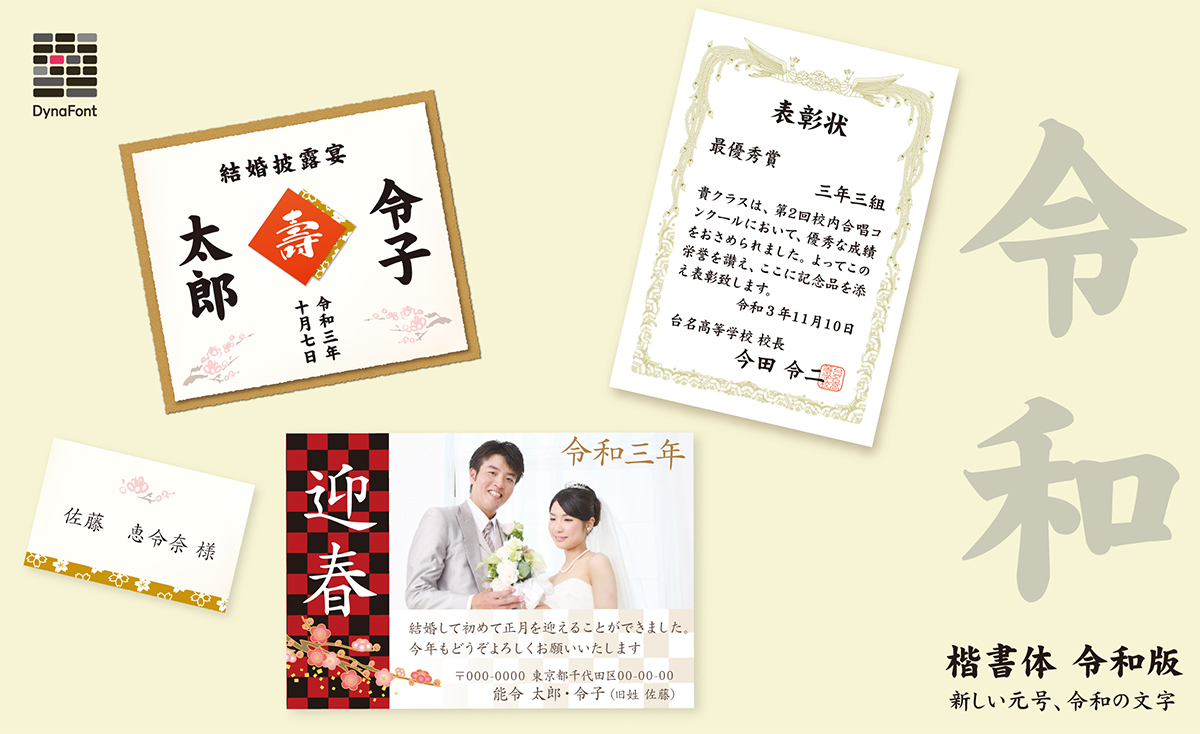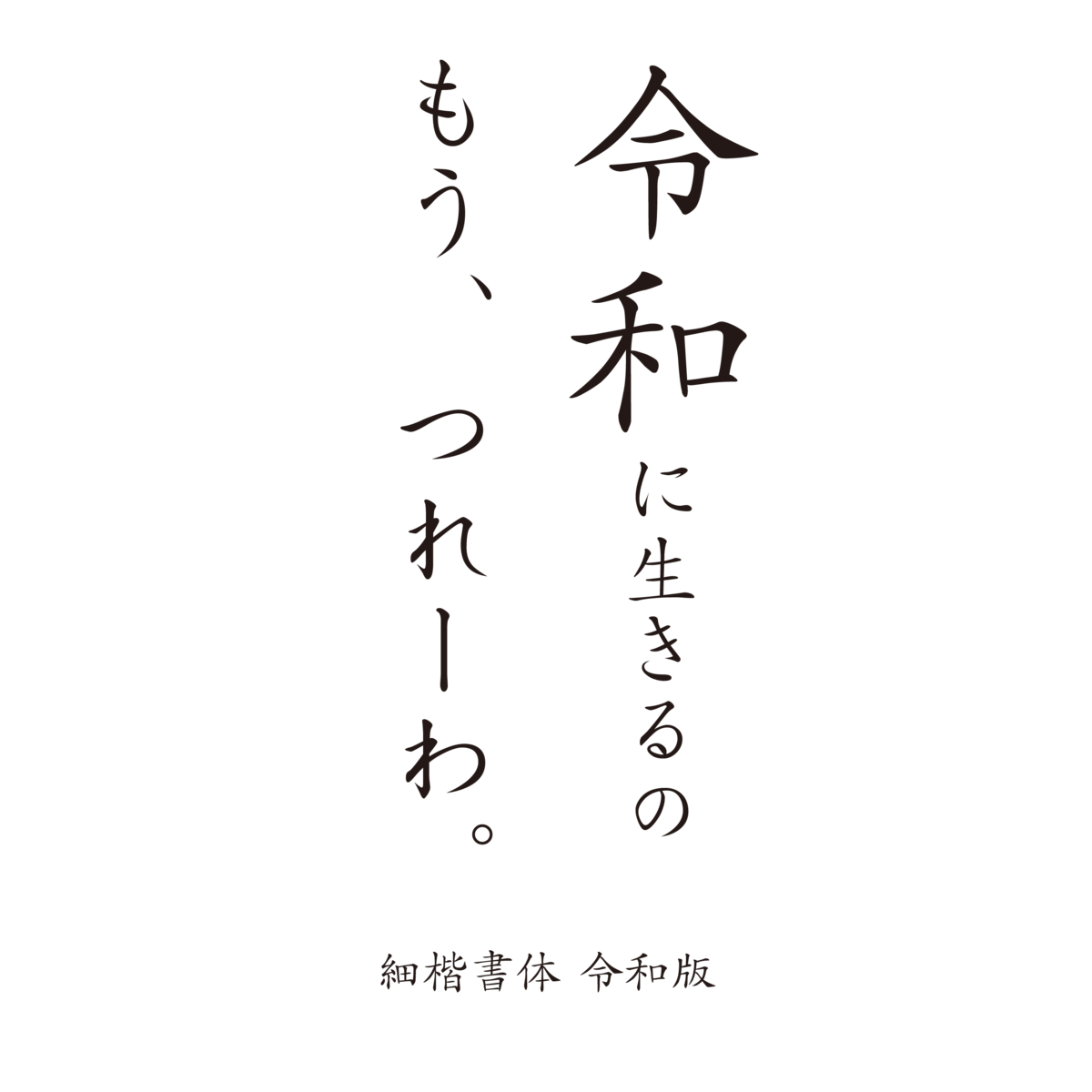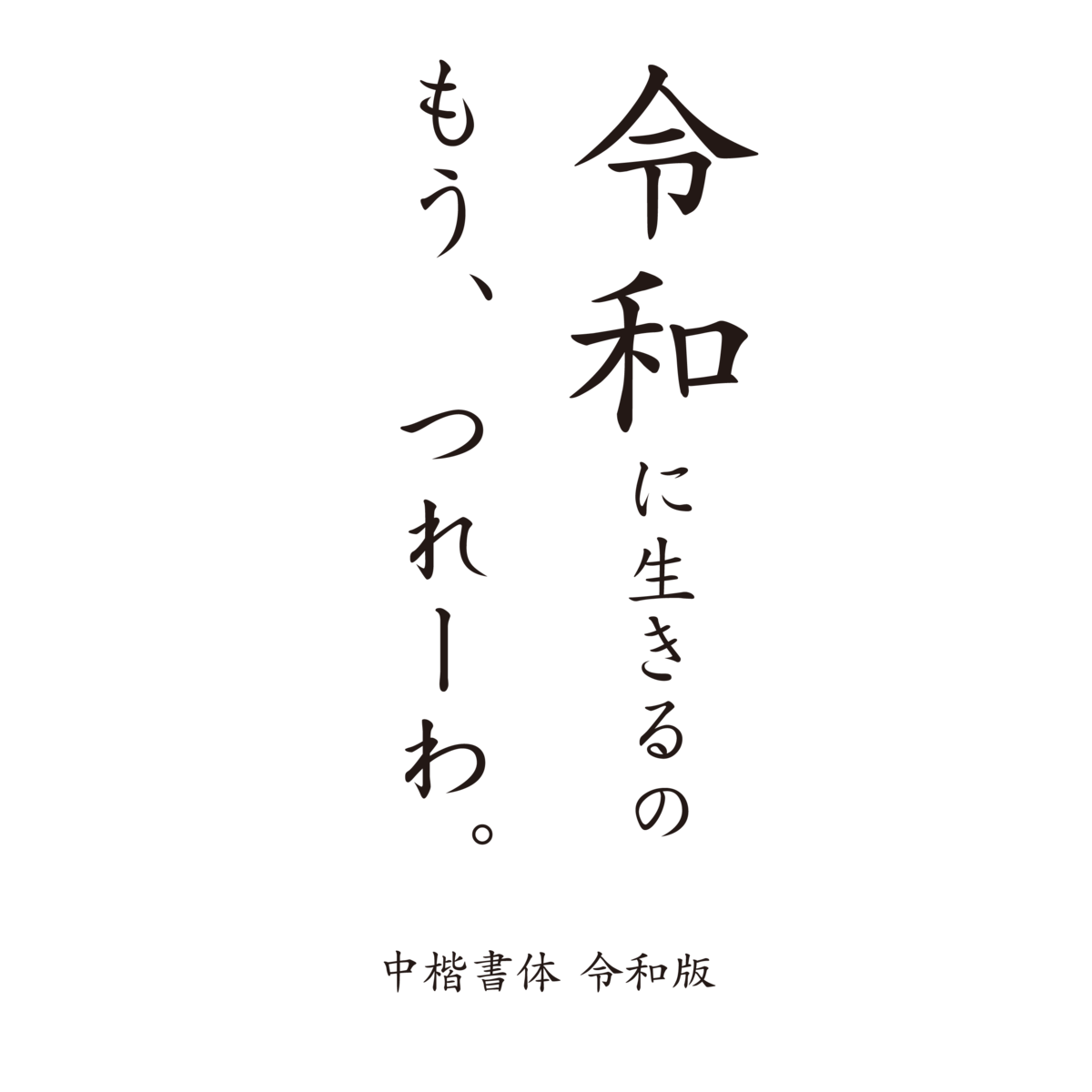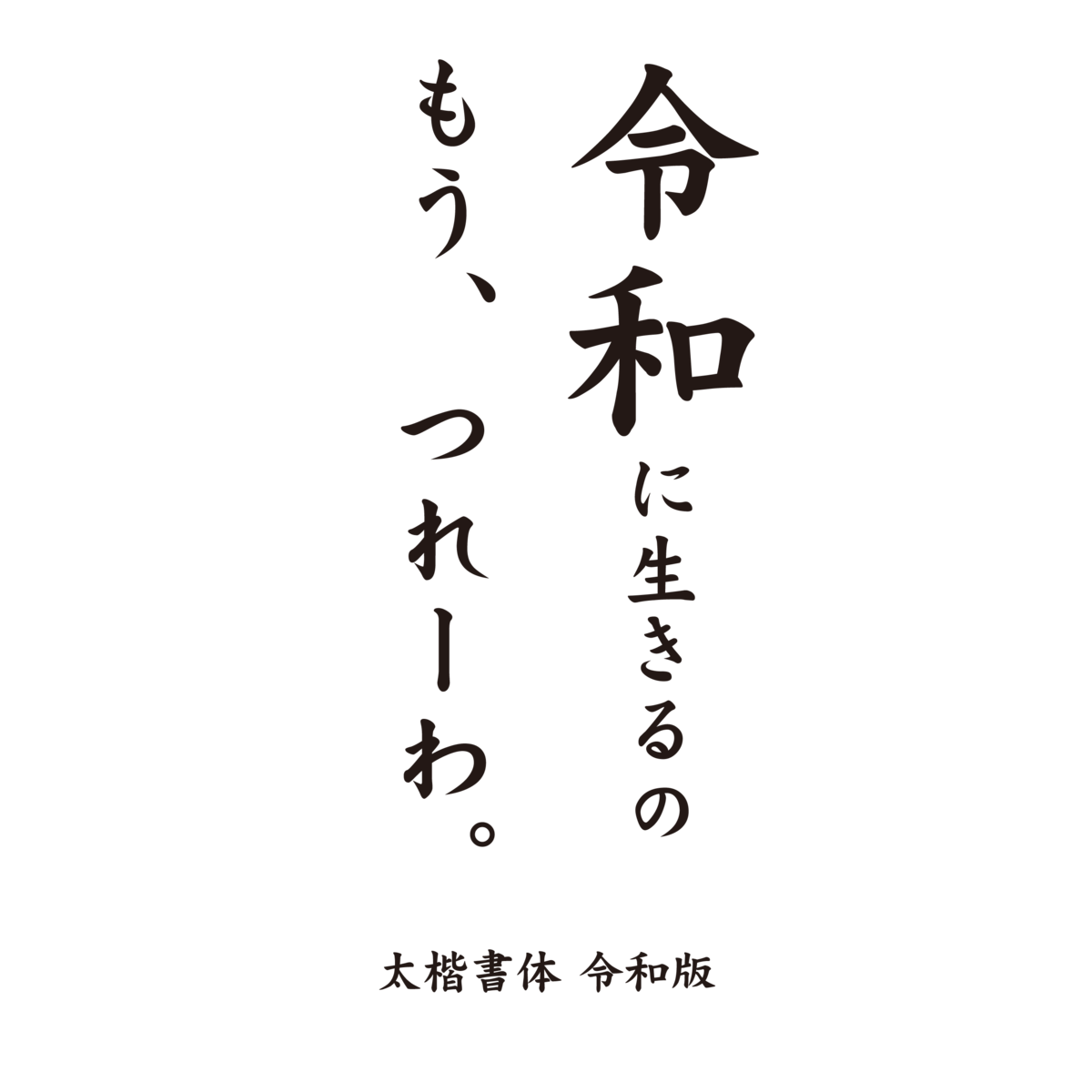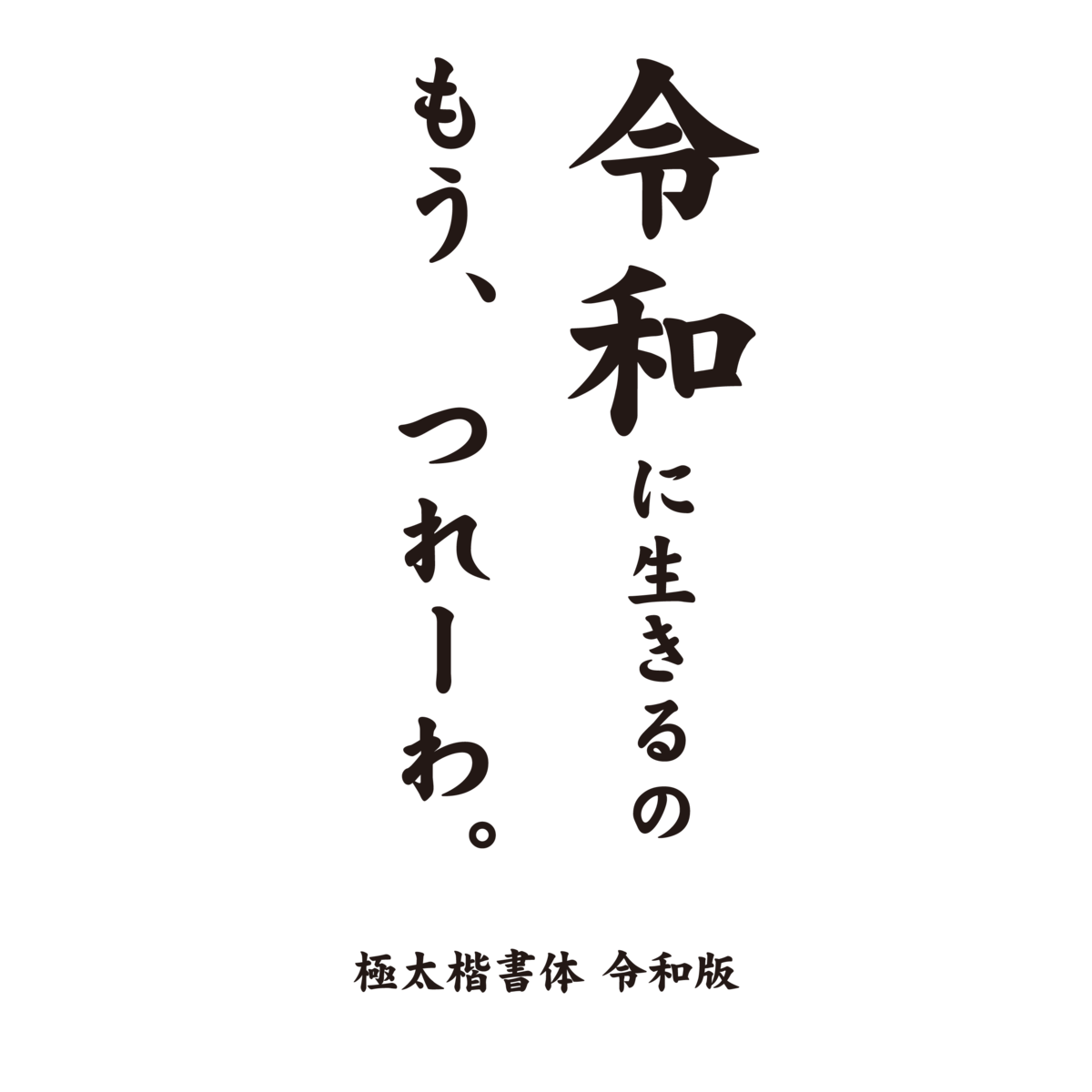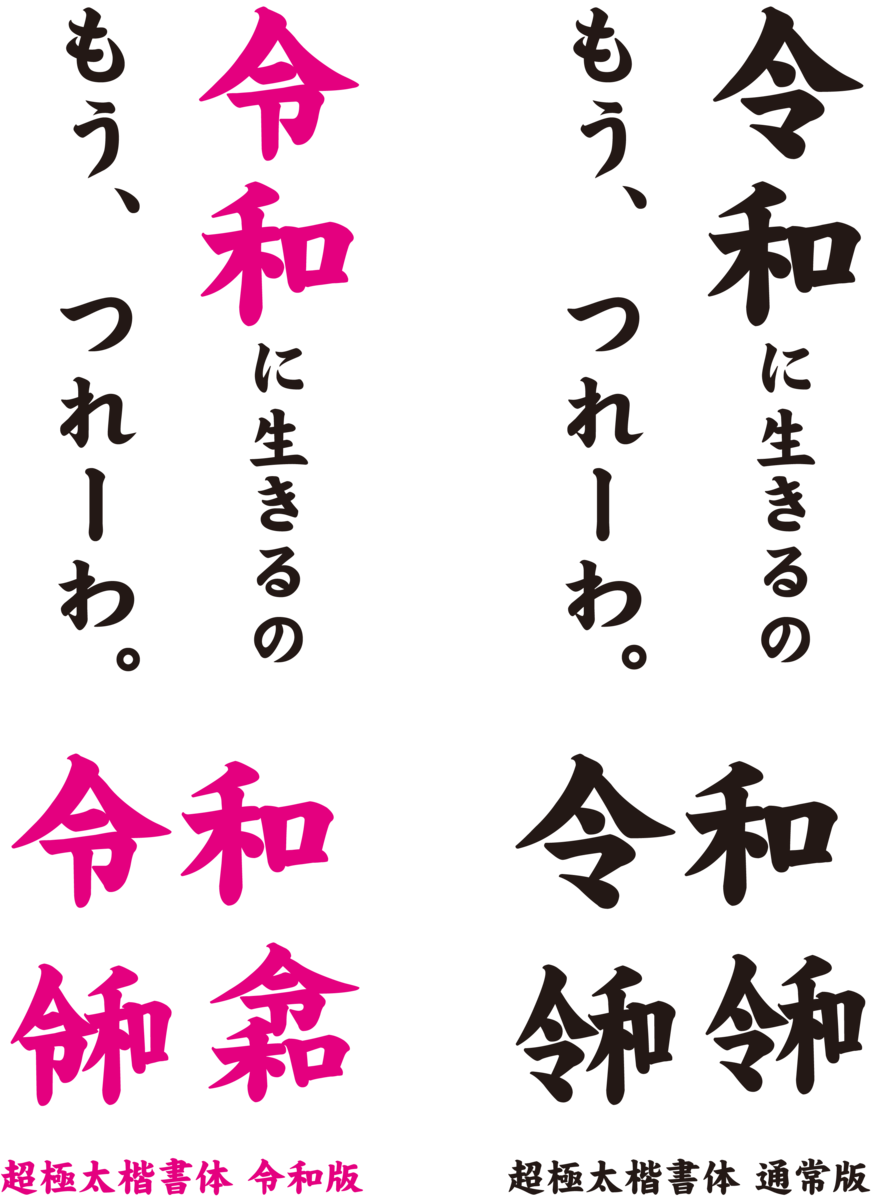
「令和」元号発表の際の字形の楷書体「楷書体令和版」
「楷書体 令和版」は、楷書体を現代でも使いやすいように視認性と判別性を高めたデザインの楷書体シリーズ「細楷書体/中楷書体/中太楷書体/太楷書体/極太楷書体/超極太楷書体」6書体を元号「令和」発表時の“令”の字形に対応させた書体。
楷書体 令和版 書体見本
楷書体令和版と通常版の字形の違い